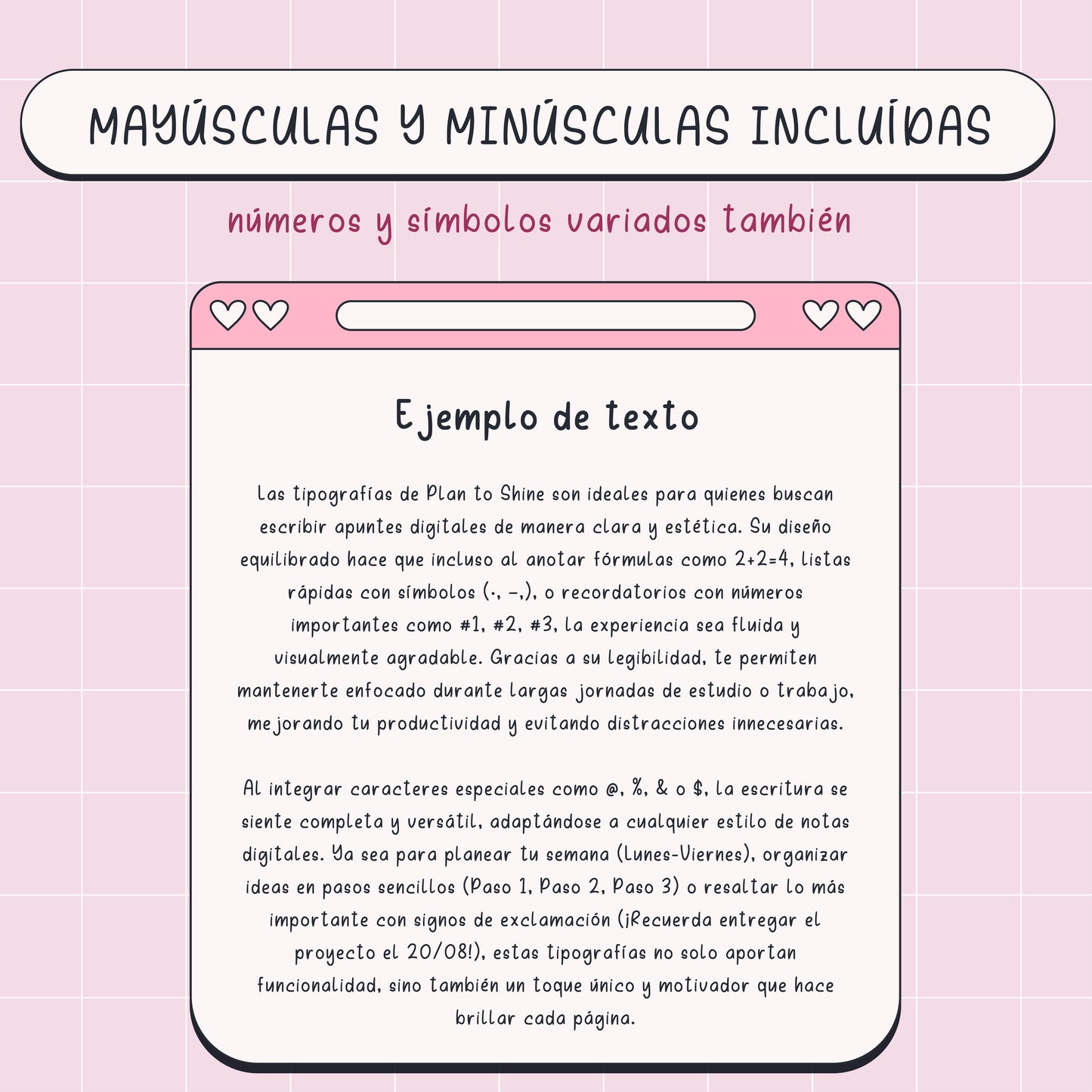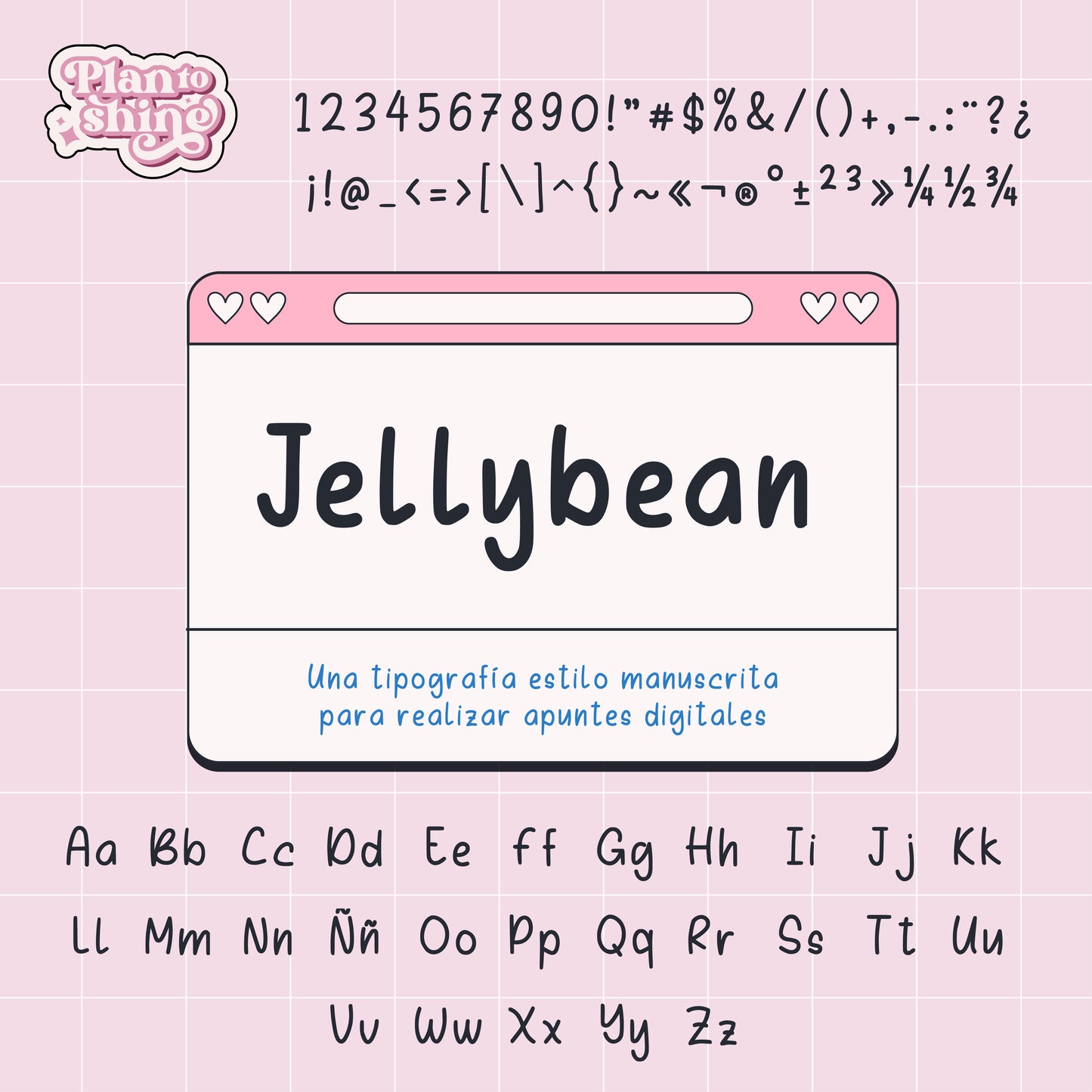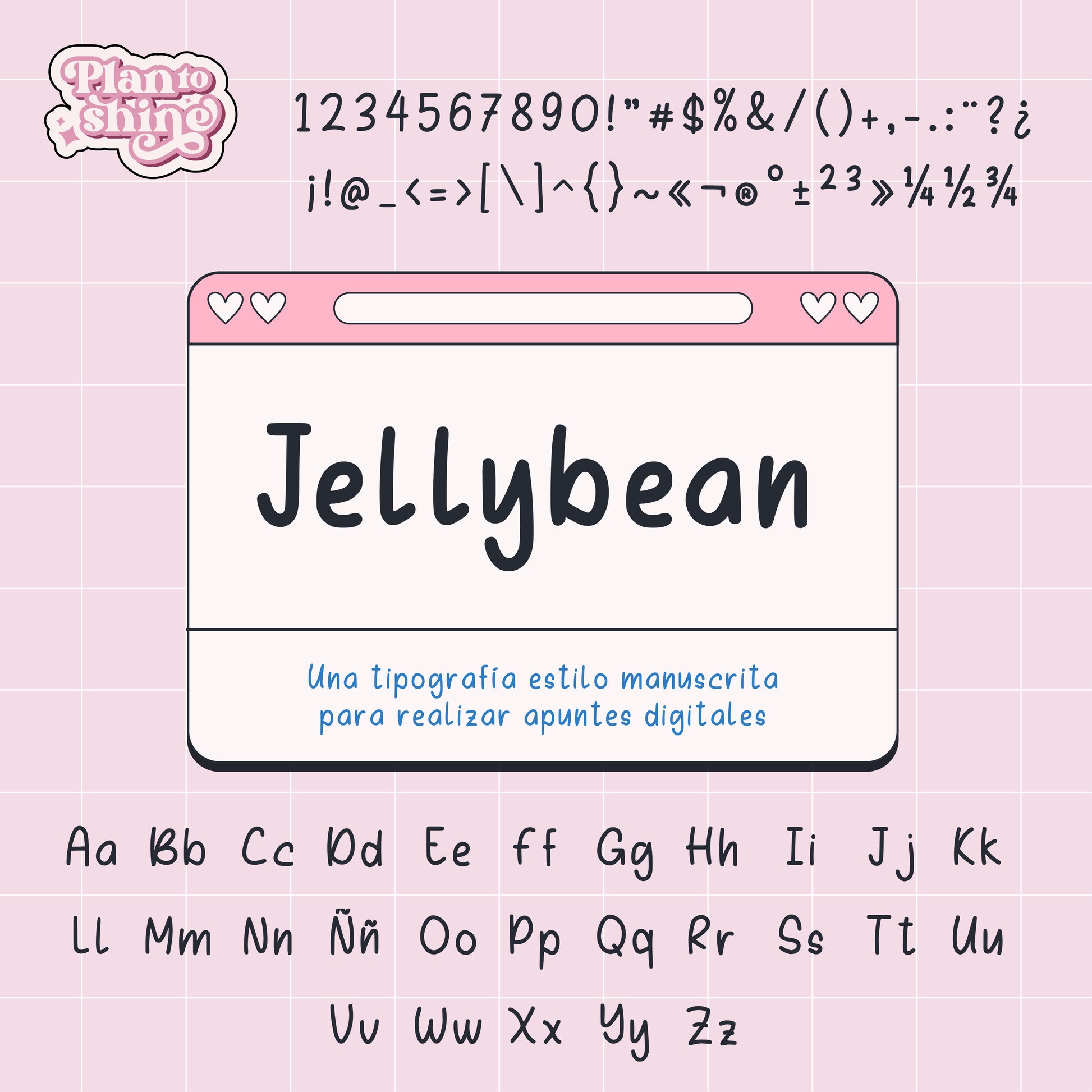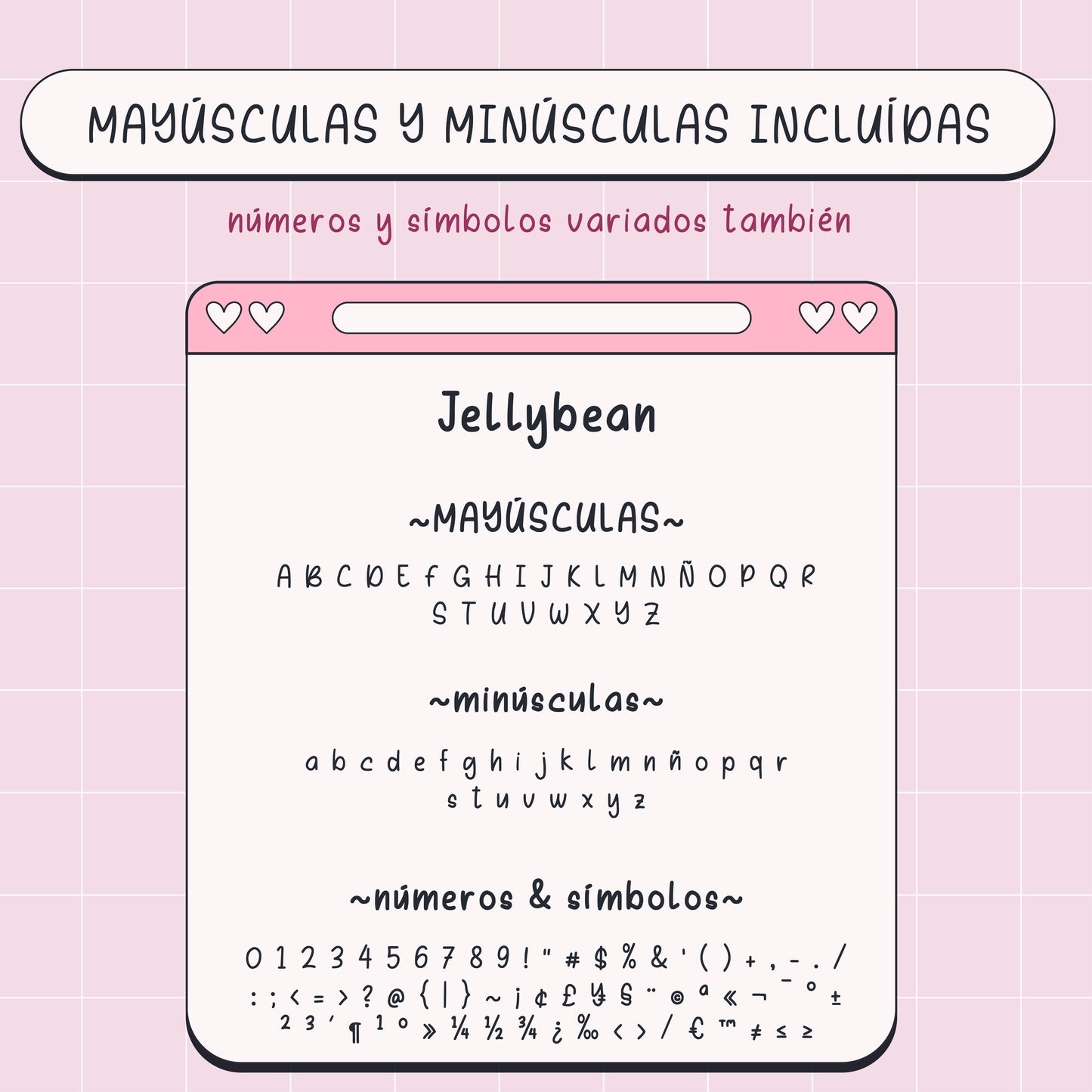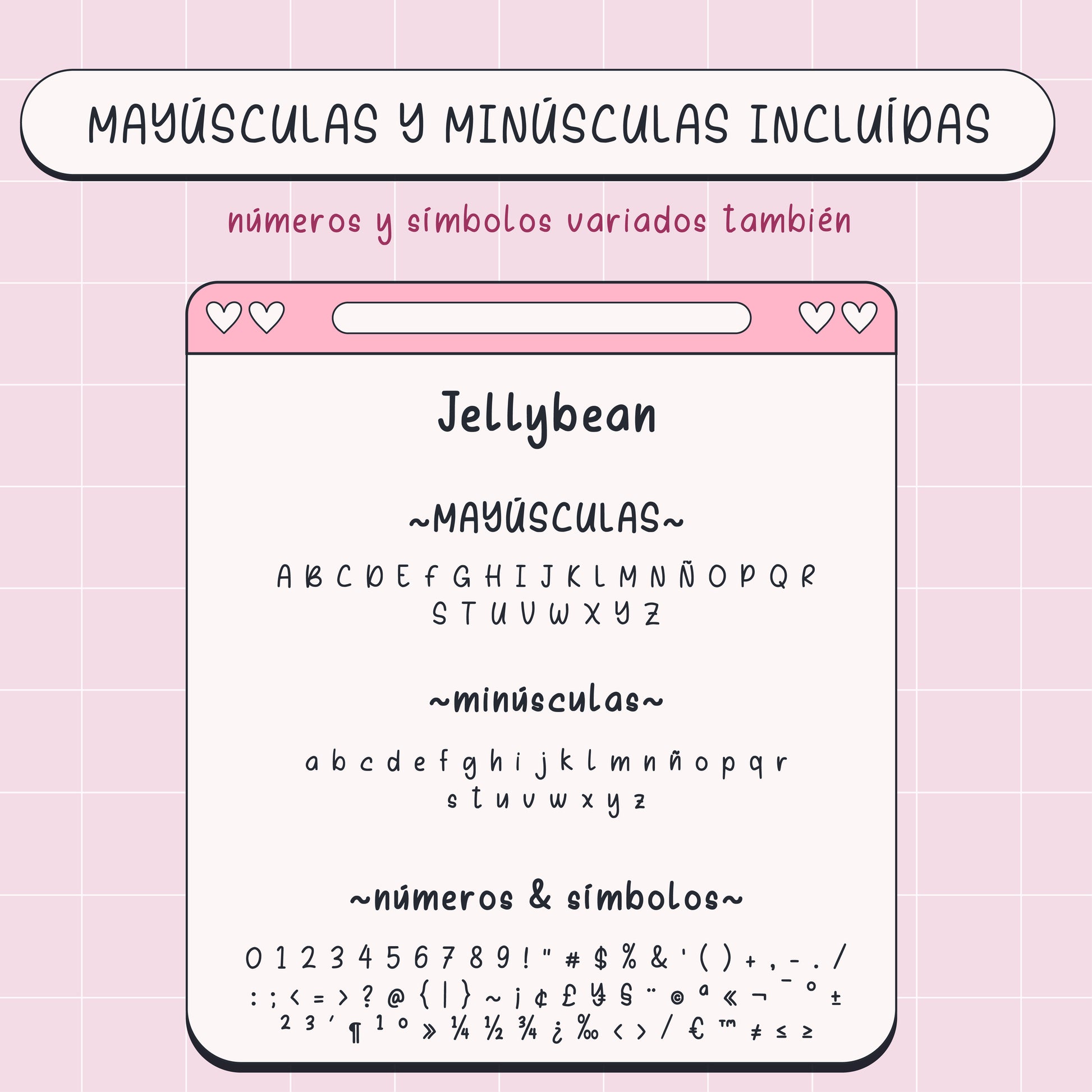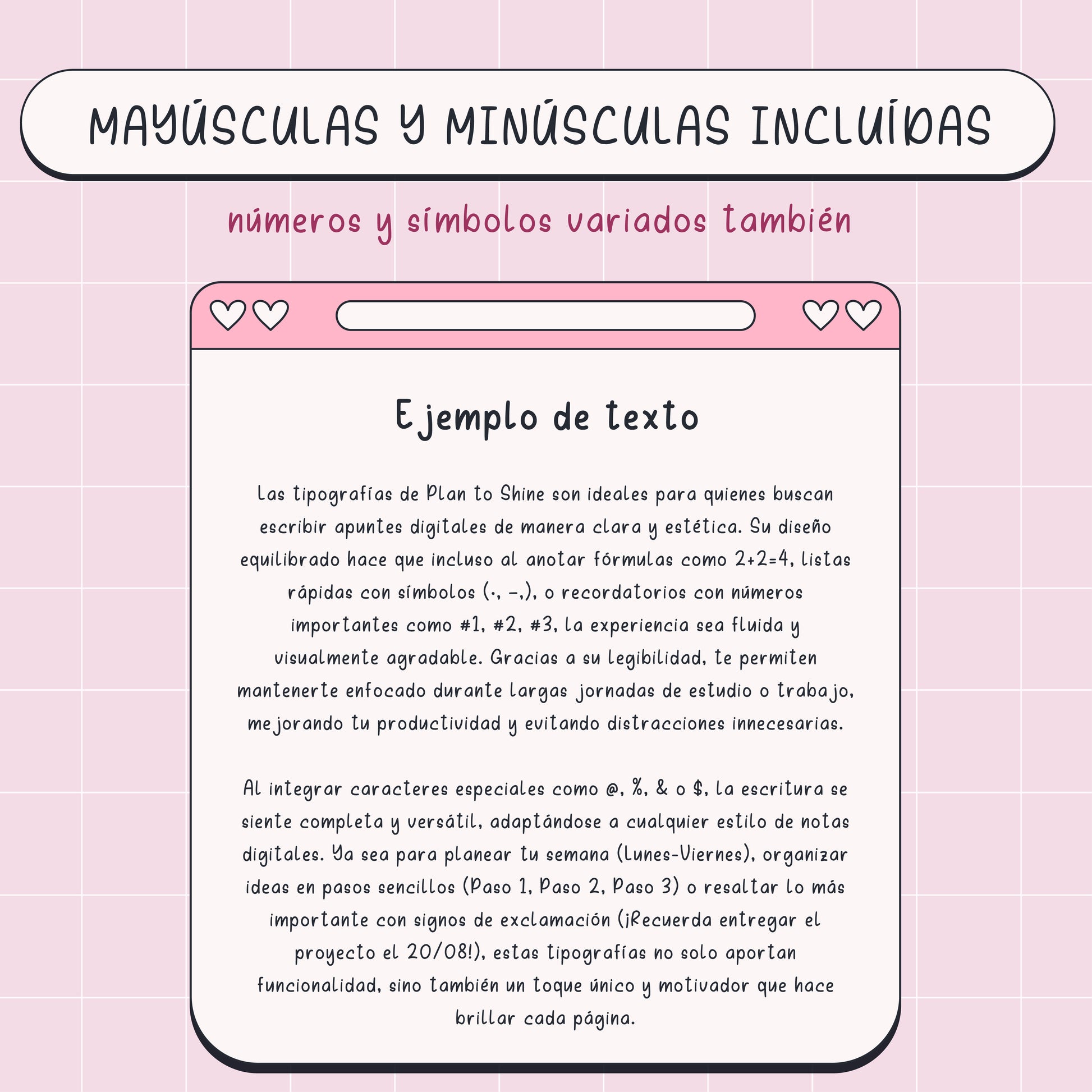
Tipografía Jellybean
Jellybean es una tipografía manuscrita dulce, limpia y fácil de leer, perfecta para crear apuntes digitales bonitos y organizados. Su estilo handwriting aporta un toque cercano y creativo, ideal para planners digitales, notas de estudio, bullet journals y contenido para redes sociales.
Esta fuente incluye mayúsculas, minúsculas, números y símbolos, ofreciendo todo lo necesario para escribir con naturalidad en proyectos digitales.
Jellybean es perfecta para estudiantes, creadores de contenido y amantes de la papelería digital que buscan una tipografía manuscrita clara y estética para tomar apuntes digitales.